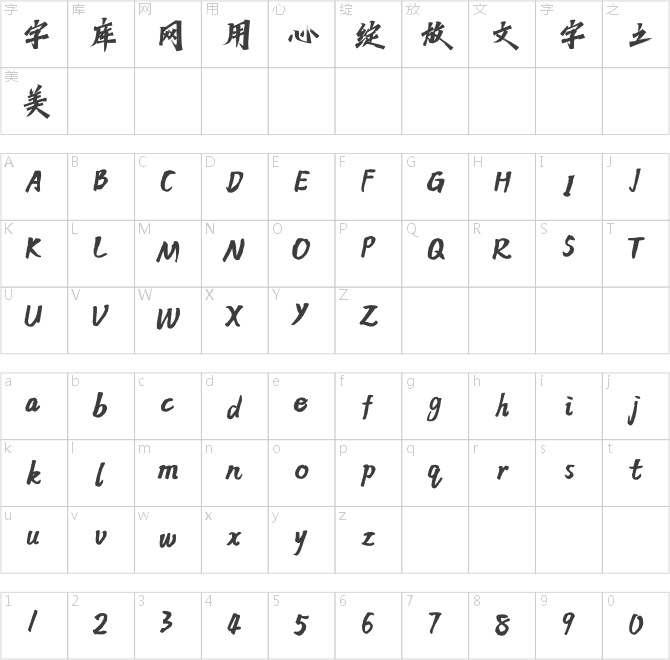
方正字跡-勁顏體 詳情頁
字體名稱: 方正字跡-勁顏
方正字跡-勁顏體
方正字跡-勁顏體介紹
勁顏體是一款創(chuàng)意書寫字體,整體結(jié)構(gòu)靈活舒展,筆畫瀟灑凌厲,尾端帶有飛白效果,重心略高,大膽追求力量的釋放,體現(xiàn)出字體年輕潮流的感覺,適用于海報、綜藝、影視劇、游戲、動漫等領(lǐng)域。